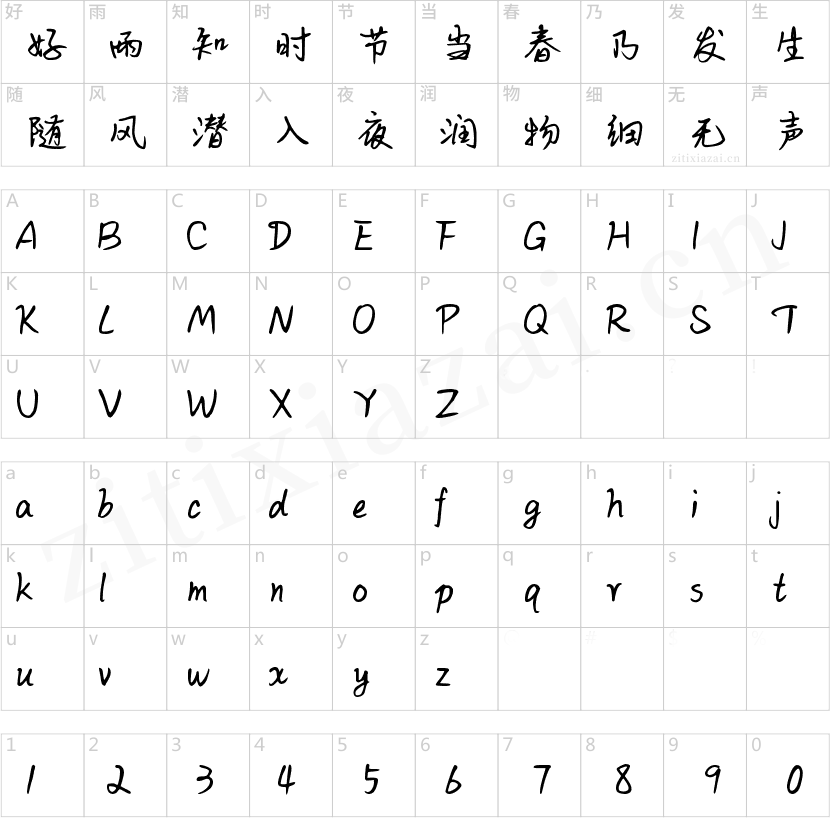
Aa叱咤风云
Aa叱咤风云字体
Aa叱咤风云是一款非常具有艺术性的字体,它的设计灵感来源于对古典艺术的研究,同时又融入了现代字体设计的元素。字形优美,笔画粗细变化自然,给人以大气、典雅的感觉。Aa叱咤风云是一款既传统又现代的字体,它的设计充满艺术感,美观大方,实用性也非常强。无论是对于设计师还是对于普通读者来说,都是一种非常不错的字体选择。Aa叱咤风云适合用于具有艺术感的场合,比如海报、宣传单张、书籍封面等。由于其字形流畅且具有动态感,也适合用于大量的文本排版,如报纸、杂志等。